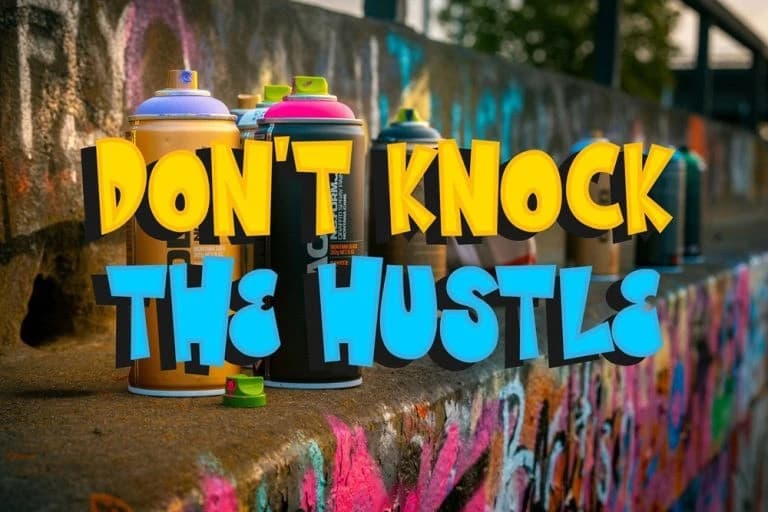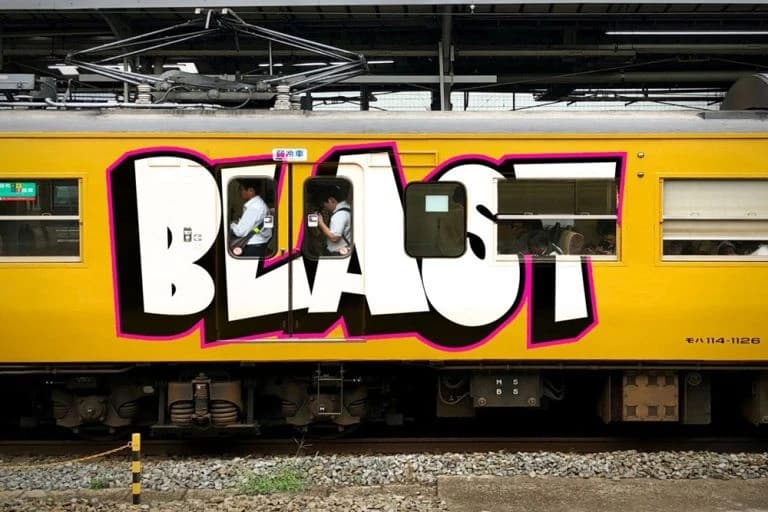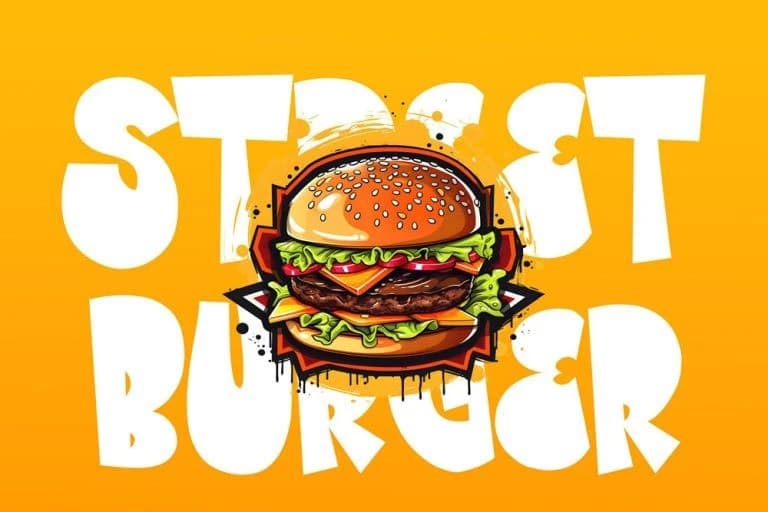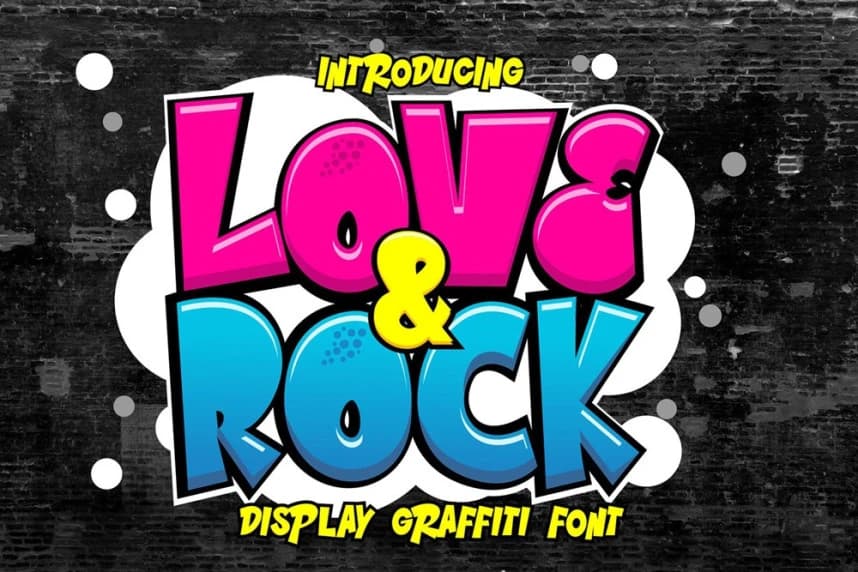
Love And Rock Font
Love And Rock Font, kalın bir graffiti gösterim yazı tipidir ve ham sokak enerjisini rock'tan ilham alan ifade ile birleştirir. Dinamik, elle çizilmiş çizgileri ve asi tavrı güçlü ve duygusal bir görsel etki yaratır; her kelimeyi canlı ve tavrı dolu hissettirir.
Love And Rock Font, ham sokak enerjisini rock ilhamlı ifade ile birleştiren cesur bir graffiti gösteri yazı tipidir. Dinamik, elle çizilmiş vuruşları ve asi tarzı güçlü ve duygusal bir görsel etki yaratır; her kelimeyi canlı ve tavır dolu hissettirir.